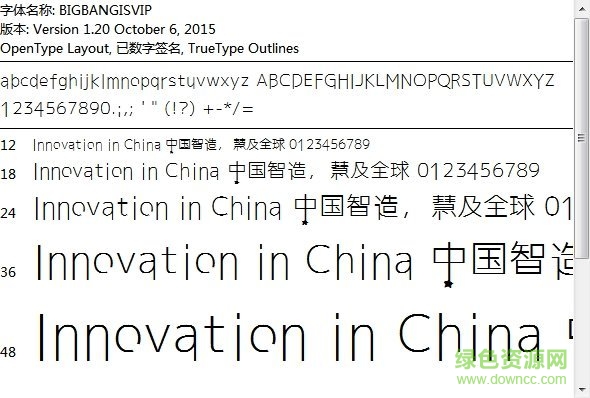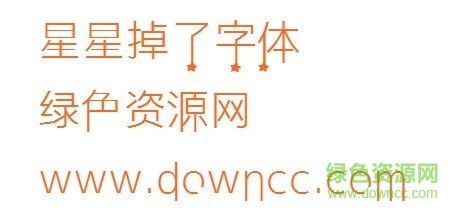
星星掉了字體是手機qq上的一款有著特色裝飾的卡通字體,字跡充滿了童真童趣的活潑體驗,可愛的星星圖案也讓你的內容更加出彩,綠色資源網(wǎng)誠意推薦!
星星掉了字體在部分漢字的下端有一個小巧可愛的實心星星圖案,而部分延長或是拉大的造型,讓文字顯得不那么對仗工整,自成一股韻味,給大家的藝術設計、海報設計帶來了獨特的視覺呈現(xiàn)!